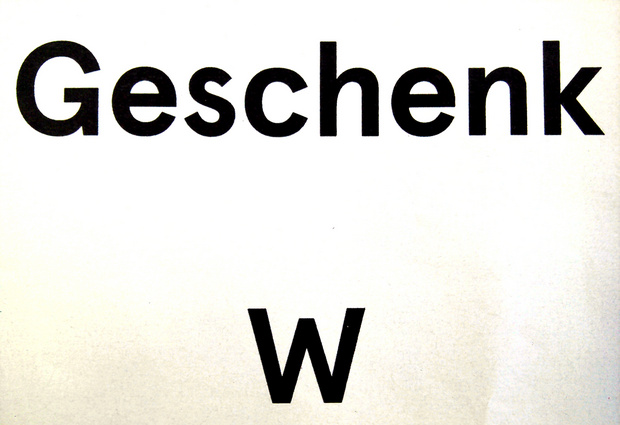
suche die Schrift der Headlines im neuen Zeit Magazin
Welche Schrift wird hier neuerdings verwendet?
Seit Mirko Borsche das Redesign gemacht hat werden im Zeit Magazin für Headlines eine mir unbekannte Serifenlose benutzt,
sonst ist alles bei der Tiemann-Antiqua-, Garamond- Kombination geblieben nur die Headlines sind moderner...
Ich habe Google, What The Font und Identyfont bereits ohne Ergebnis durchforstet, hoffentlich könnt ihr mir helfen!
im orangenem Kasten auf Borsches Seite auch gut zu erkennen